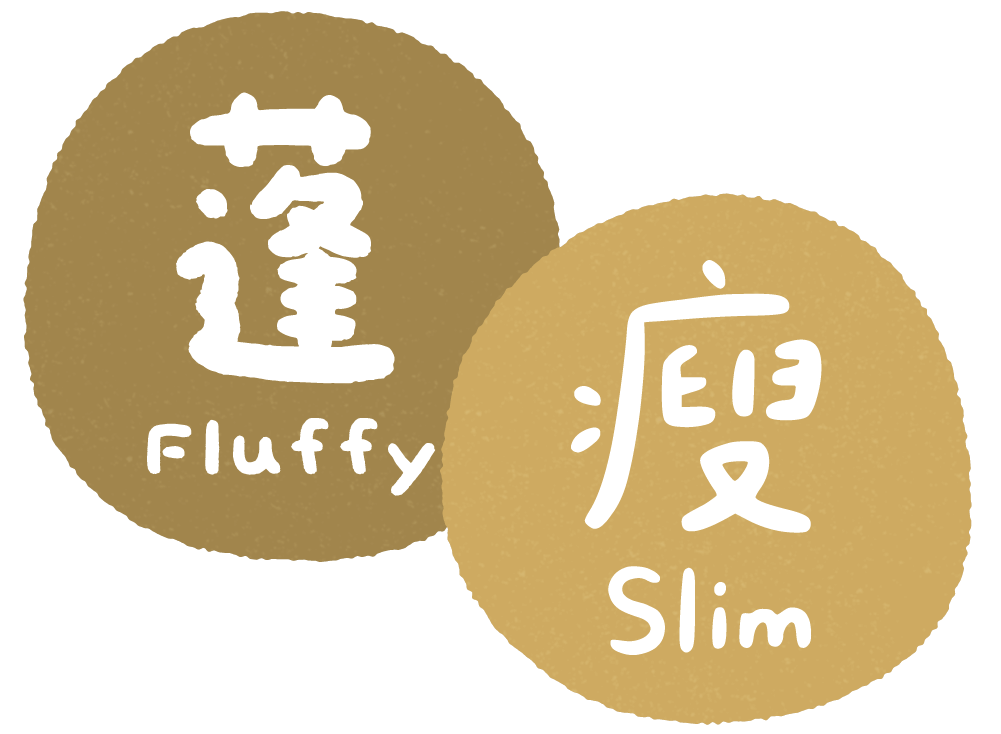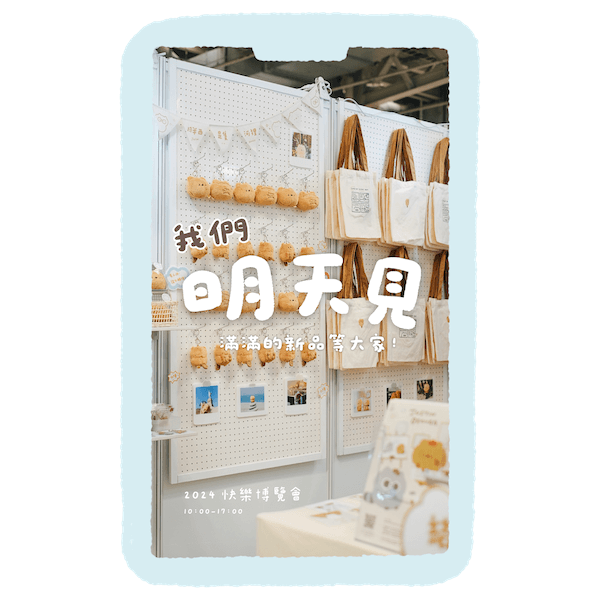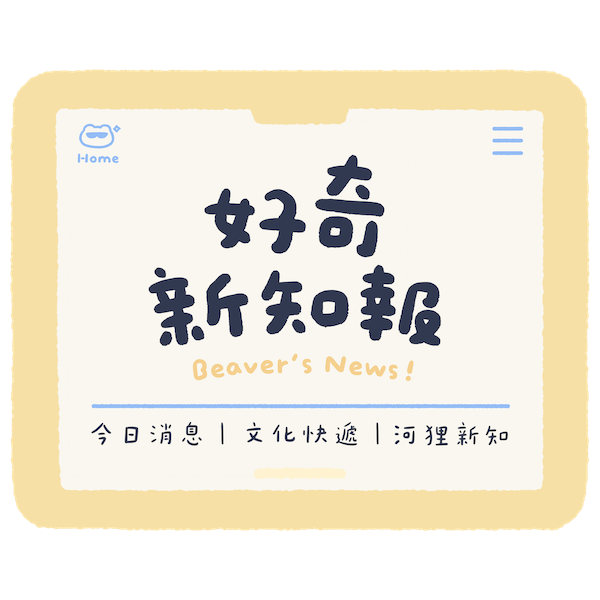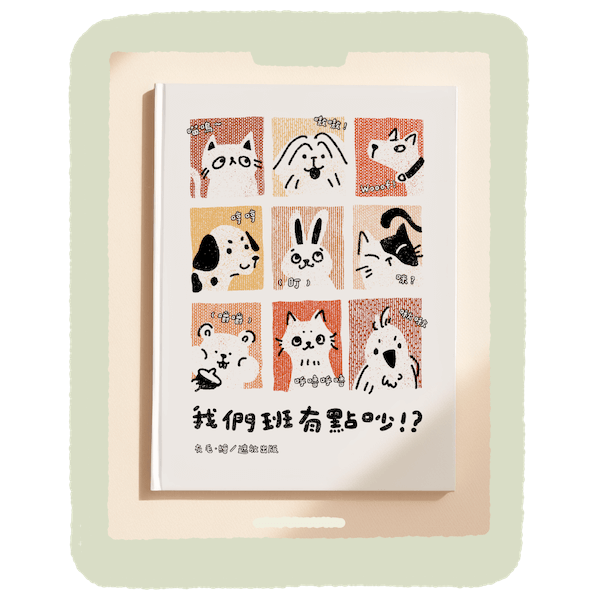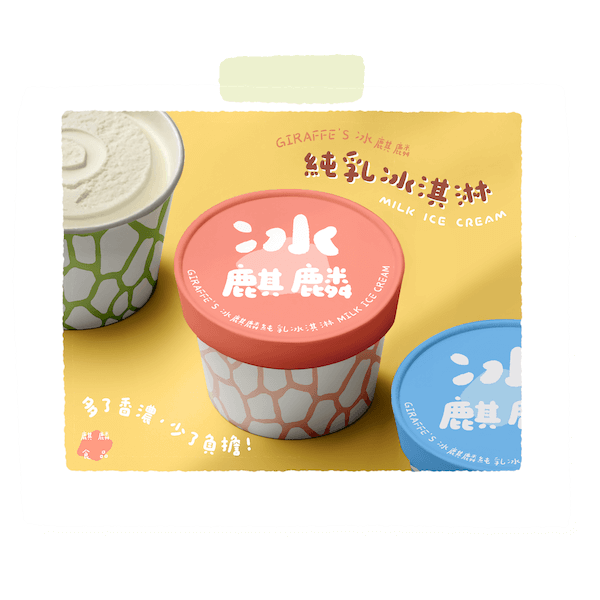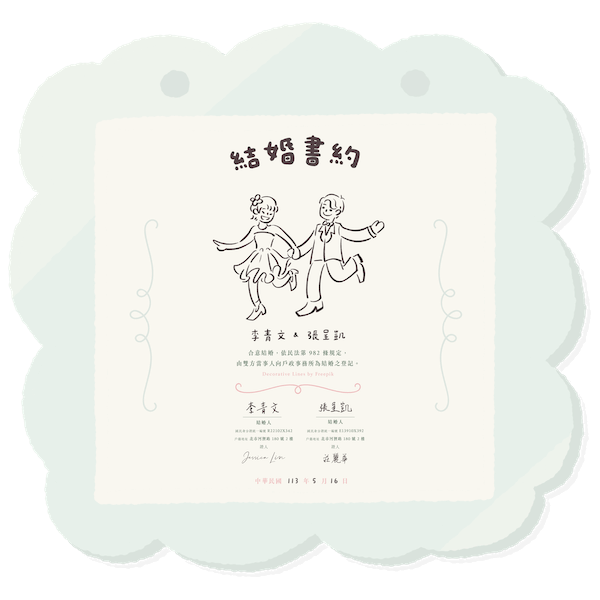
胖西手寫體
2 種字重
胖胖圓圓、柔軟 Q 彈、親切自然的可愛字體。
同時擁有兩種粗細,好搭好用,還有專屬 Emoji!
胖西手寫體適用於各種生活場景,以及社群動態。
胖西是胖胖的咖啡色河狸,圓圓二頭身,有扁扁的叉叉尾巴。喜歡和浣熊睏睏、小河狸胖咚玩在一起。認真感受生活,努力做事也用力耍廢!大部分時間都很快樂(但常常跌倒),心情不好的話就用吃和睡覺解決:3 字如其狸,柔軟真誠(突然進入毛遂自薦時間)出現在 IG 限動、課表筆記、小標籤,療癒滿分。讓我陪你分享生活中的每個片刻~